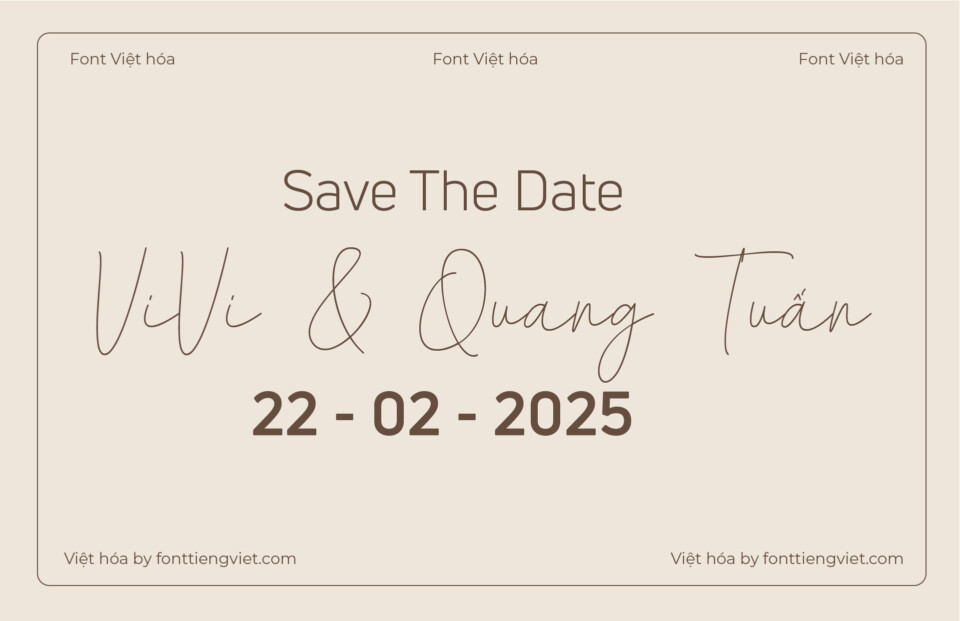
Font Việt hóa 1FTV VIP Shine Brightly – Sự lựa chọn hoàn hảo cho thiết kế học đường
Giới thiệu bộ Font Việt hóa 1FTV VIP Shine Brightly
Trong thế giới đồ họa hiện đại, việc lựa chọn Font Chữ phù hợp đóng vai trò quan trọng để truyền tải thông điệp một cách hiệu quả nhất. Bộ Font Việt hóa 1FTV VIP Shine Brightly là một trong những lựa chọn hàng đầu cho các bạn học sinh và giáo viên khi cần tìm kiếm sự sáng tạo. Với đường nét thanh mảnh, hiện đại nhưng không kém phần rực rỡ, bộ font này giúp các slide bài giảng hay các bài báo tường trở nên sinh động và thu hút ánh nhìn hơn bao giờ hết.
Đặc điểm nổi bật của bộ font
Bộ font này được thiết kế với phong cách thanh lịch, giúp các văn bản tiếng Việt không bị lỗi dấu – một vấn đề thường gặp khi sử dụng các font ngoại nhập. Font Việt hóa 1FTV VIP Shine Brightly hỗ trợ đầy đủ các ký tự đặc biệt, giúp người dùng tự do thể hiện ý tưởng mà không lo ngại về kỹ thuật. Sự kết hợp giữa tính thẩm mỹ và tính ứng dụng cao khiến nó trở thành công cụ đắc lực cho các bạn trẻ yêu thích sáng tạo nội dung số.
Cách ứng dụng Font Việt hóa 1FTV VIP Shine Brightly hiệu quả
Sử dụng trong trình chiếu và in ấn
Khi thiết kế bài thuyết trình, bạn có thể dùng font này cho các tiêu đề chính để tạo điểm nhấn mạnh mẽ. Đối với các sản phẩm in ấn như thiệp mời, bìa sách hay bảng tin trường học, bộ chữ này mang lại cảm giác chuyên nghiệp và tươi mới. Độ tương phản tốt của các nét chữ giúp người đọc dễ dàng theo dõi nội dung ngay cả ở khoảng cách xa.
Mẹo nhỏ khi thiết kế
Hãy kết hợp bộ font này với các gam màu sáng để làm nổi bật tinh thần “Shine Brightly”. Việc điều chỉnh khoảng cách dòng và kích thước chữ hợp lý sẽ giúp bố cục trang giấy trở nên hài hòa, mang lại trải nghiệm thị giác tốt nhất cho người xem.
Kết luận về bộ font chất lượng